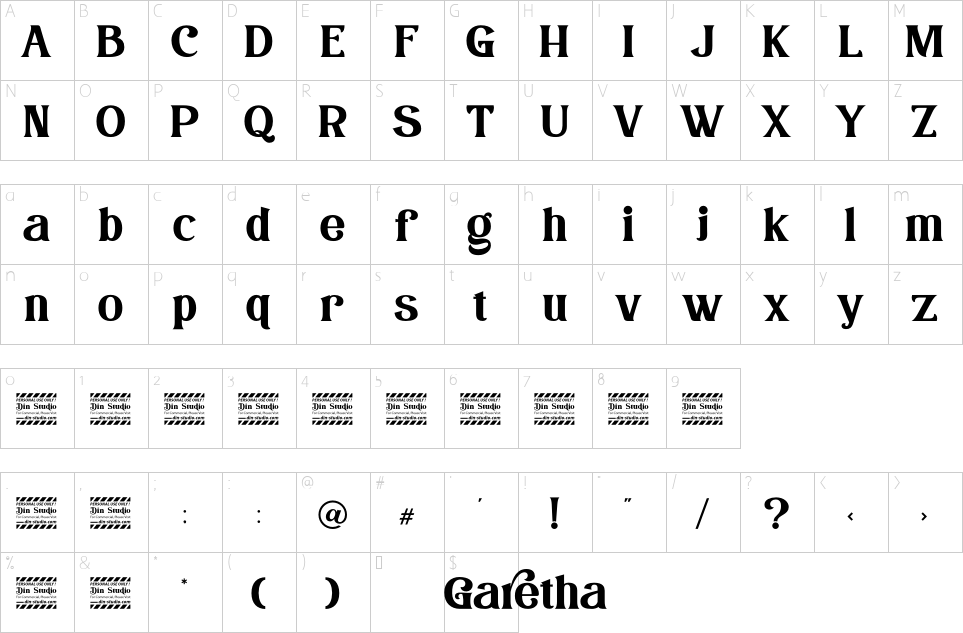
Aqui está uma descrição curta e envolvente para a página de download da fonte Garetha: Garetha é uma elegante e minimalista fonte que oferece um toque contemporâneo às suas criações digitais. Desenvolvida pela Din Studio, esta elegante opção gráfica pode ser facilmente integrada em projetos de design gráfico para torná-los ainda mais profissionais. Essa fonte apresenta uma simplicidade que se sobrepõe a um charme sofisticado, perfeitamente adaptável a qualquer estilo ou contexto. Ela é ideal para aplicações tanto digitais quanto impressas, desde cartazes e panfletos até design de sites responsivos. Com seu design minimalista e arrojado, Garetha será uma escolha inteligente para aqueles que buscam um visual contemporâneo em suas criações. Descubra por si mesmo a essência única desta fonte e sinta-se encorajado a experimentá-la para criar uma experiência gráfica ainda mais inovadora. Descarregue Garetha hoje e descubra o poder de design que esta elegante fonte pode lhe oferecer. Sua simplicidade e funcionalidade permitem-lhe explorar sua potencial em um vasto leque de projetos, seja ele digital ou impresso.